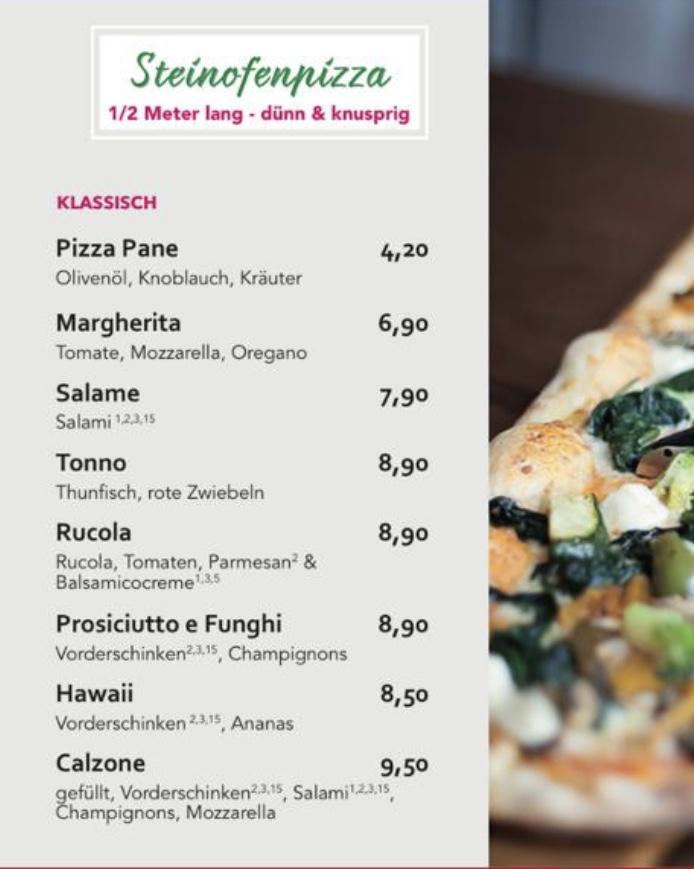
Suche Schrift für Speisekarte
kann mir jemand vielleicht weiterhelfen. Ich gestalte eine moderne Speisekarte, jedoch kenne ich mich nicht allzu sehr mit der Sprache der Schrift aus.
Es sollte eine serifenlose, gut lesbare Schrift sein. Habt ihr eventuell Ideen. Vielleicht auch noch interessant, die Karte wird auf ein Brett geklemmt.
So sieht es aktuell aus...
Auf mich wirkt der weiße Kasten oben nicht modern, sondern eher, nun ja, altbacken. Ich würde Kasten und Rahmen weglassen, alles linksbündig setzen (mit »Klassisch«) und auch noch mal die Schrift von Steinofenpizza überdenken, die wirkt auch nicht gerade modern. Am einfachsten (und »modernsten«) wäre vielleicht, auch hierfür einfach einen Schrift derselben serifenlosen Schriftfamilie zu nehmen, die sonst verwendet wird.
[Nur ein Einwurf: im "Prosciutto" hat sich ein i zu viel eingeschlichen.]
Herzlichen Dank. Ich werde deine Ansätze mal umsetzen... hast du eventuell  hinsichtlich der Typo  noch ne Idee?
Noch eine Nörgelei: Unter Margherita heißt es "Tomate", anderswo "Tomaten". Das solltest Du vielleicht angleichen, sofern die Margherita nicht tatsächlich nur mit einer Tomate gemacht wird. Das wäre aber eine traurige Pizza 😉
Du verstehst das nicht. Es handelt sich um ein sogenanntes Portmanteau-Wort, in dem auch noch ein »Prosit« mit drinsteckt.
Jetzt helft ihr doch mal mit der Schriftwahl … :tutor:
Ich werf mal die Roboto in die Runde, eine Light als Fließtext und Condensed oder Slab zum Auszeichnen …
Ich werf dann mal ganz notorisch eine meiner Lieblingsschriften in den Raum: https://www.myfonts.com/fonts/adobe/hypatia-sans-pro/
Ich weiß jetzt grad nicht, wo man die lizensieren kann, aber die dürfte bei Typekit dabei sein. Durch die vielen Schnitte bräuchte man auch nur eine Schrift und hätte dennoch reichlich Abwechselung: Pizza Pane in Regular oder Semibold, leicht gesperrt, und die Zutatenliste dann in einer leicht lichteren Kursive (abhängig von der Beleuchtungssituation).
Gut, modern ist die Hypatia nicht wirklich, doch wichtiger sind doch noch Fragen wie:
• Welche Emotion soll die Schrift transportieren?
• Wie ist das Gesamtbild der Karte
• Was strahlt der Restaurant aus
• Wie ist die Beleuchtungssituation
• Wer ist die Zielgruppe
• ...
Hast Du ein anständiges Briefing bekommen? Oder eine Bedarfs-/Markenanalyse gemacht? Nur "modern" finde ich ein büschen dürftig. Modern in Bezug auf was?
https://www.behance.net/gallery/2727177/Villa-Didot-(Free-Font) mit https://www.myfonts.com/fonts/stereotypes/florence/ zum Beispiel – ohne damit die vernünftige  Anregung von @Phoibos zu einem fundierten Konzept übergehen zu wollen … damit hättest Du etwas, was grob gesagt unter anderem auf italienisch, handgemacht und lockere Atmosphäre abzielt
Und genau hier frage ich mich, ob das gerade zum Restaurant-Konzept passt, denn denn Pizzen in Meterlängen sind irgendwie nicht so typisch italienisch handgemacht. Wie breit ist die dann eigentlich? Irgendwie hab ich da so eine Hightech-Pizza im Kopf: Ein Teigband-Extruder spukt ein schmales Teigband in Halbmeterlänge aus, ein Förderband transportiert das unter dem Tomatensoßen-Dusierer zur Belagstation, wo der Gast aus den GN-Behätern die gewünschten Beläge auswählt, die vor seinen Augen aufs Teigband kommen. Ist der Belag abgeschlossen, läuft das Band weiter, um den nächstewn Teigband-Abschitt zur Belagstation zu förden, während die fertig belegte auf eine Endloskette aus Pizza-Steinen, sie einen Tunnelofen durchläuft, um dann auf die Ausgabestation zu gleiten. - Aber das ist eben Kopfkino bei einen halben Meter lang...
Deswegen auch:
Das Konzept muss schon erst vorliegen, wenn unsere Tipps passen sollen. Sonst tappen wir im Dunkeln.
Hmm, vielleicht würde die Schraffur der Villa Didot den Fließbandcharakter ja wunderbar symbolisieren? 8-)